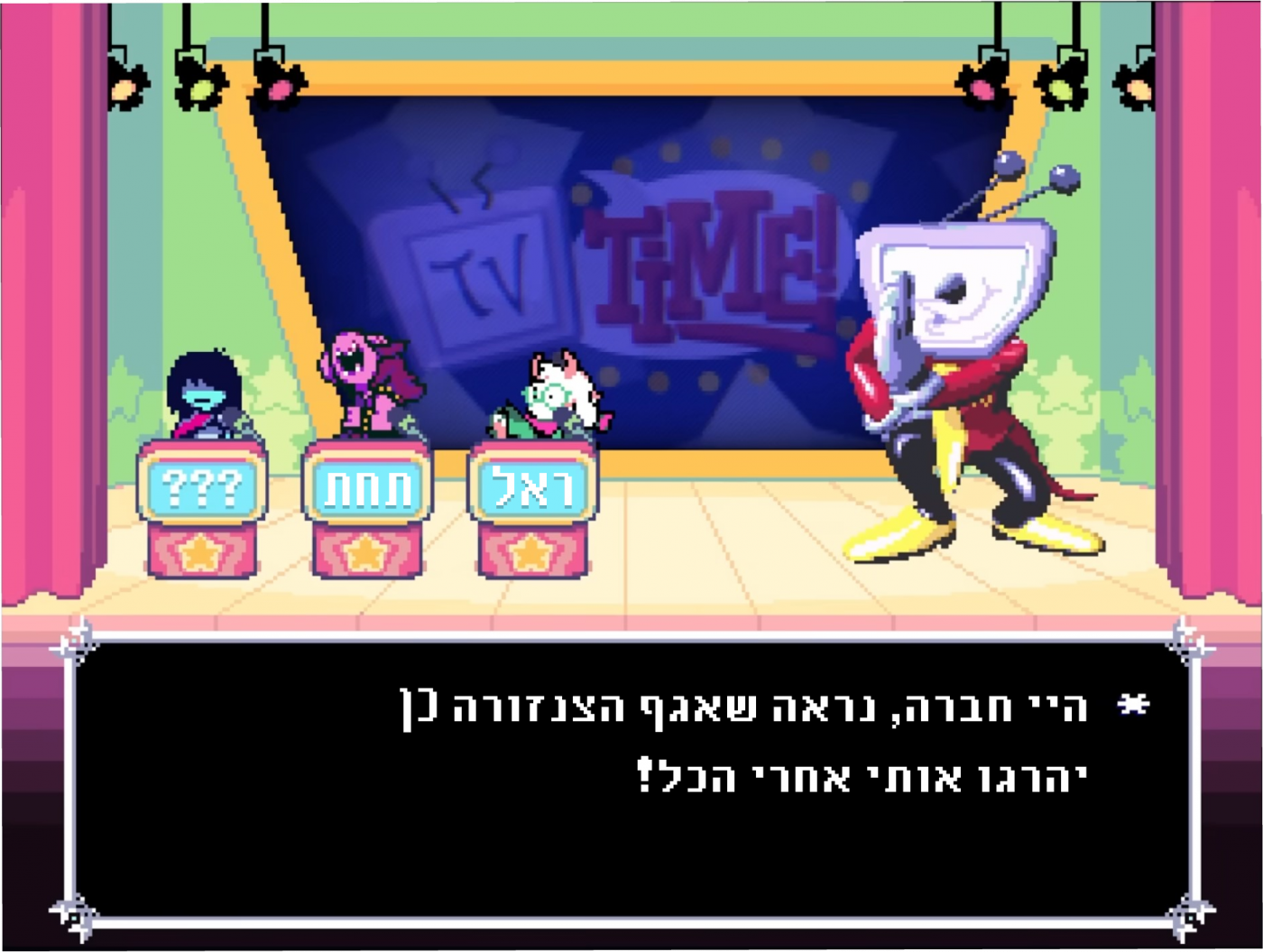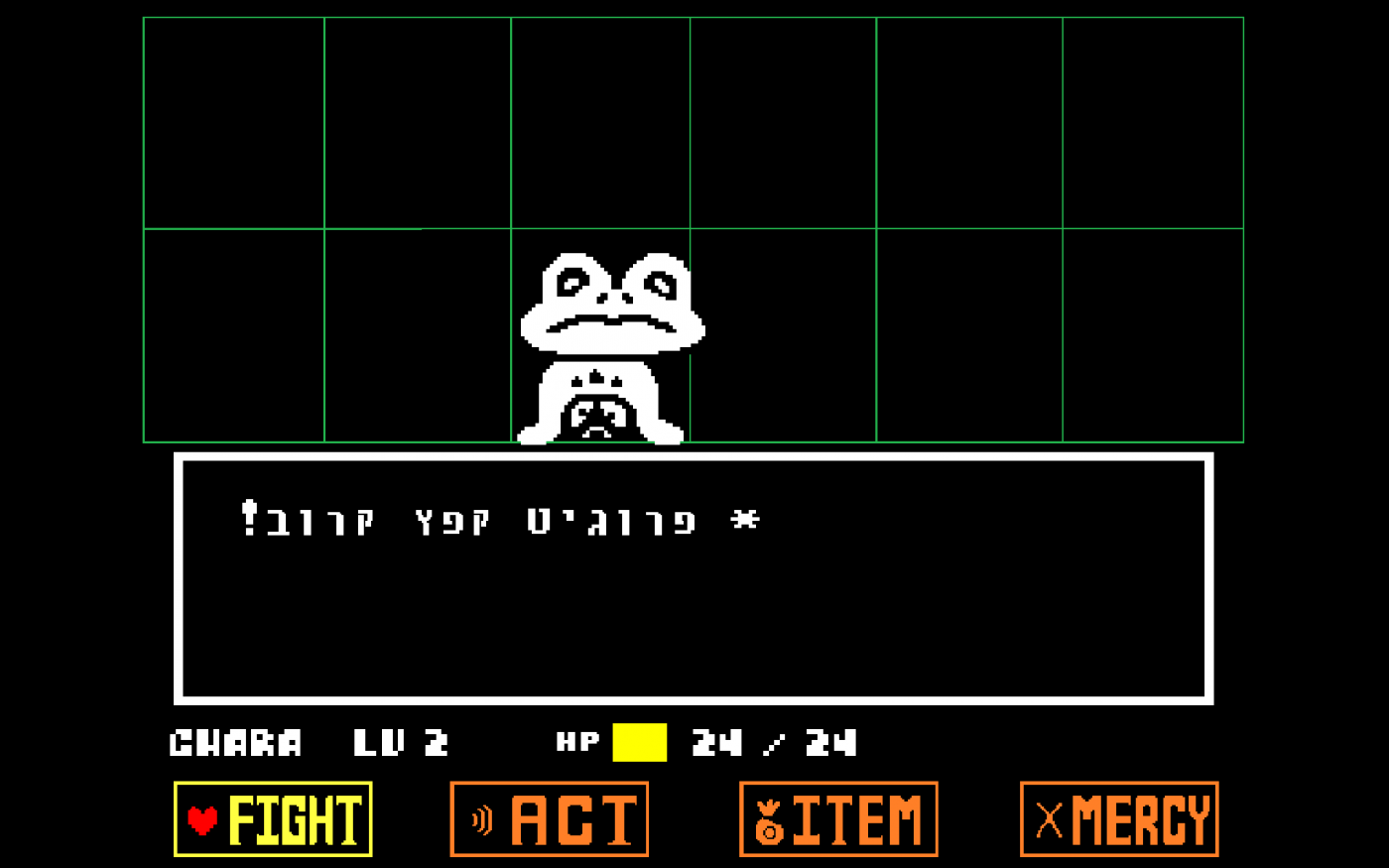
• פונט שיצרתי כך שיהיה דומה ויתאים לפונט שבמשחק אנדרטייל. השימוש בגופן חופשי, רק קחו בחשבון שכל התוים שלא בעברית לקוחים מאנדרטייל.
דוגמה לשימוש בגופן